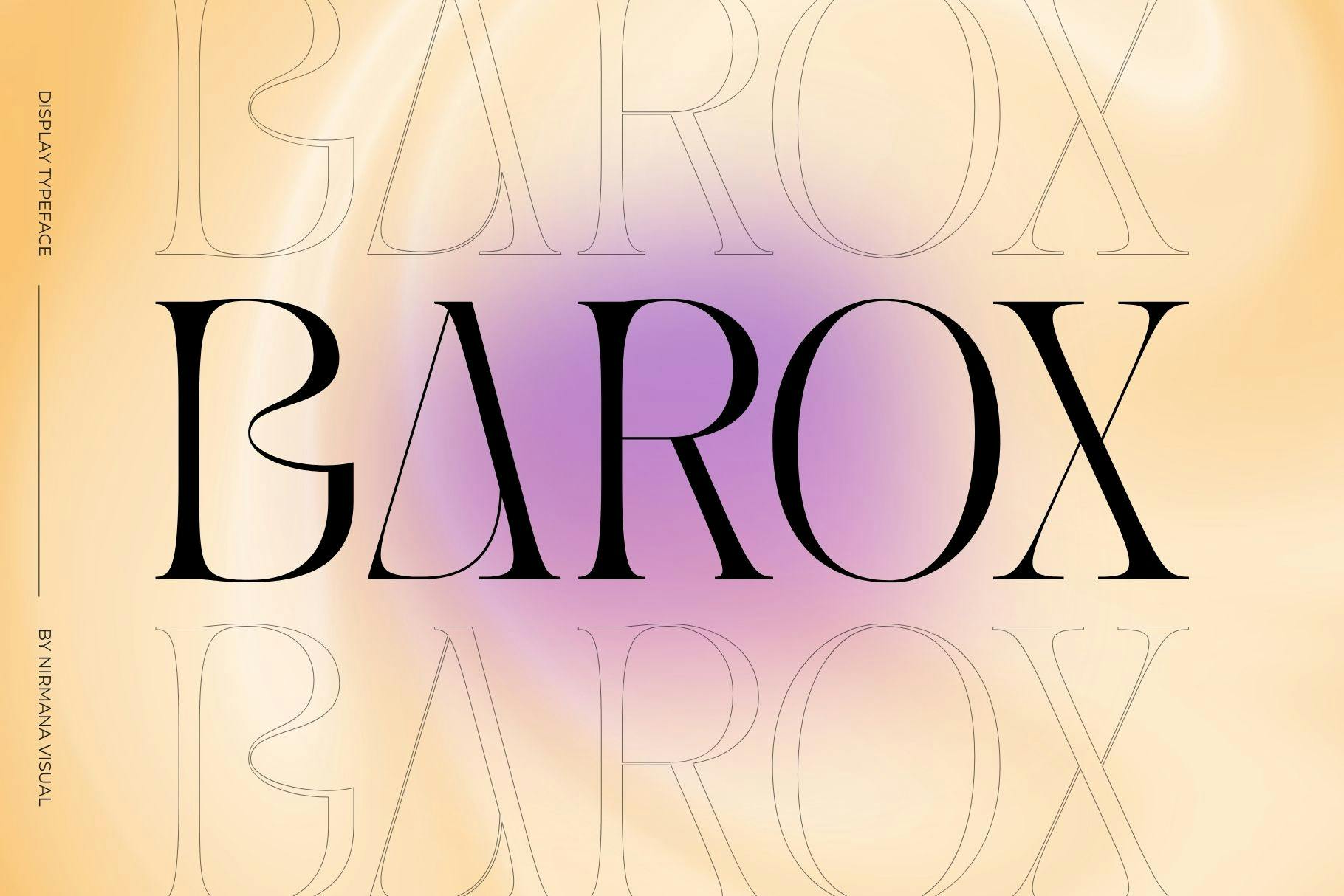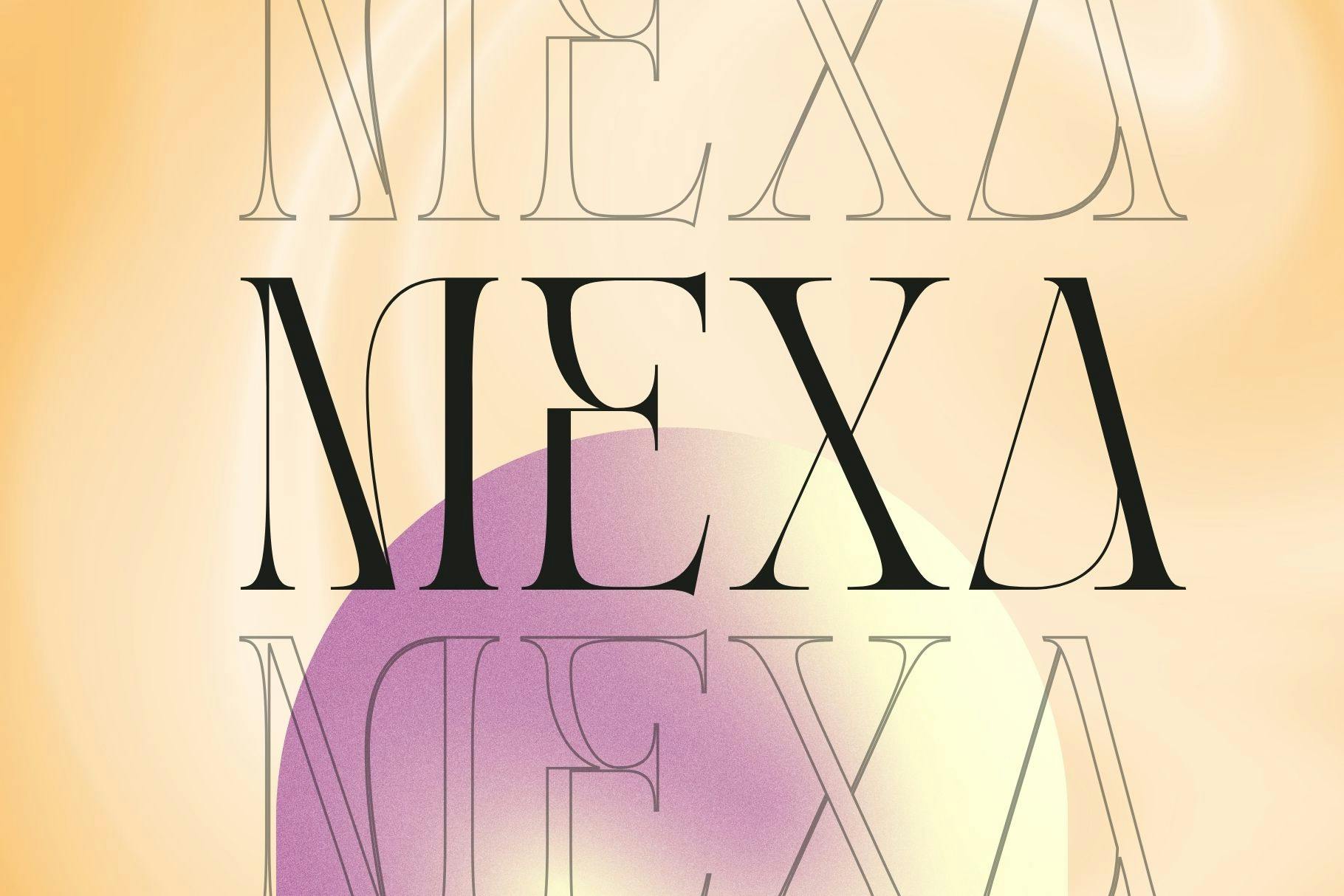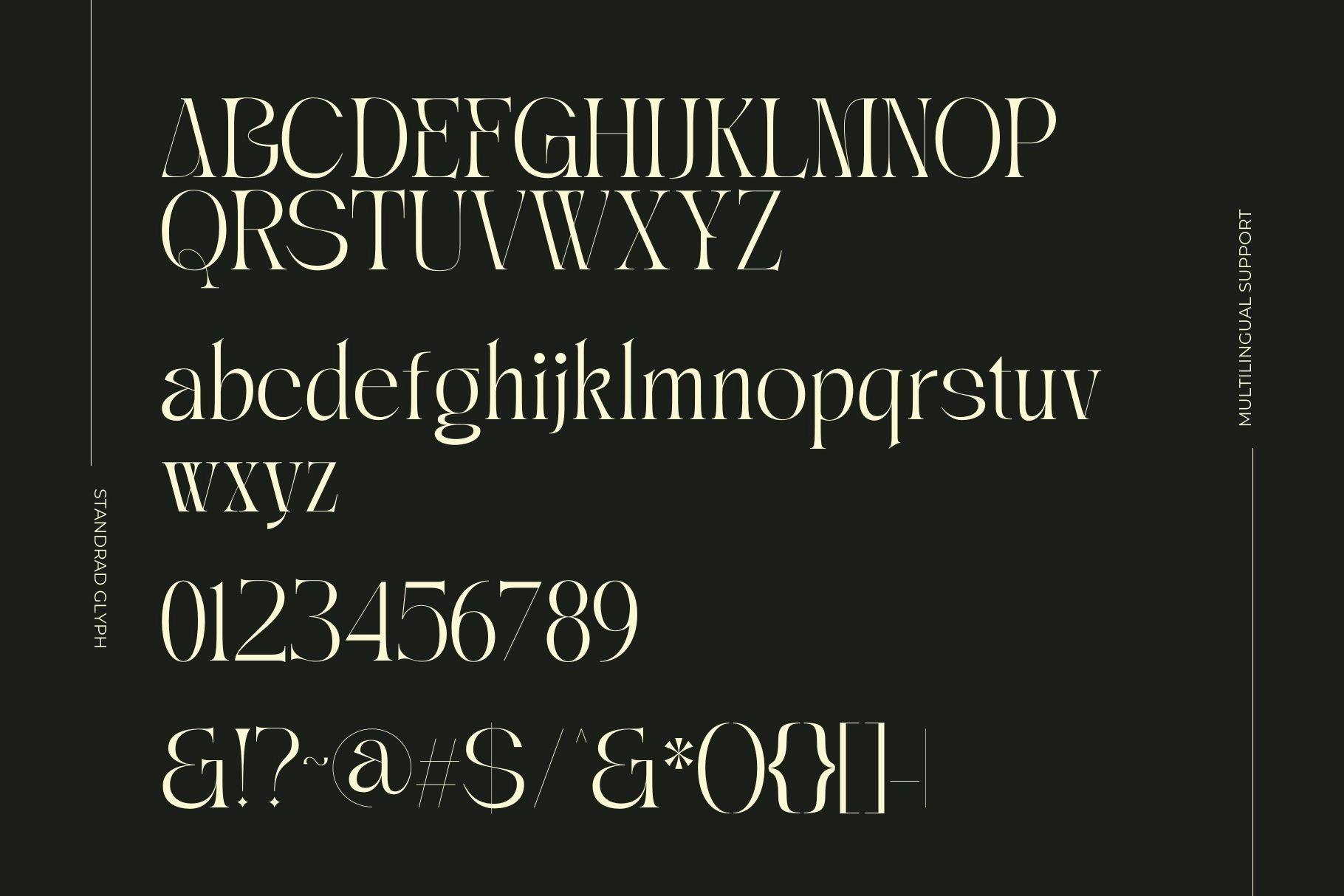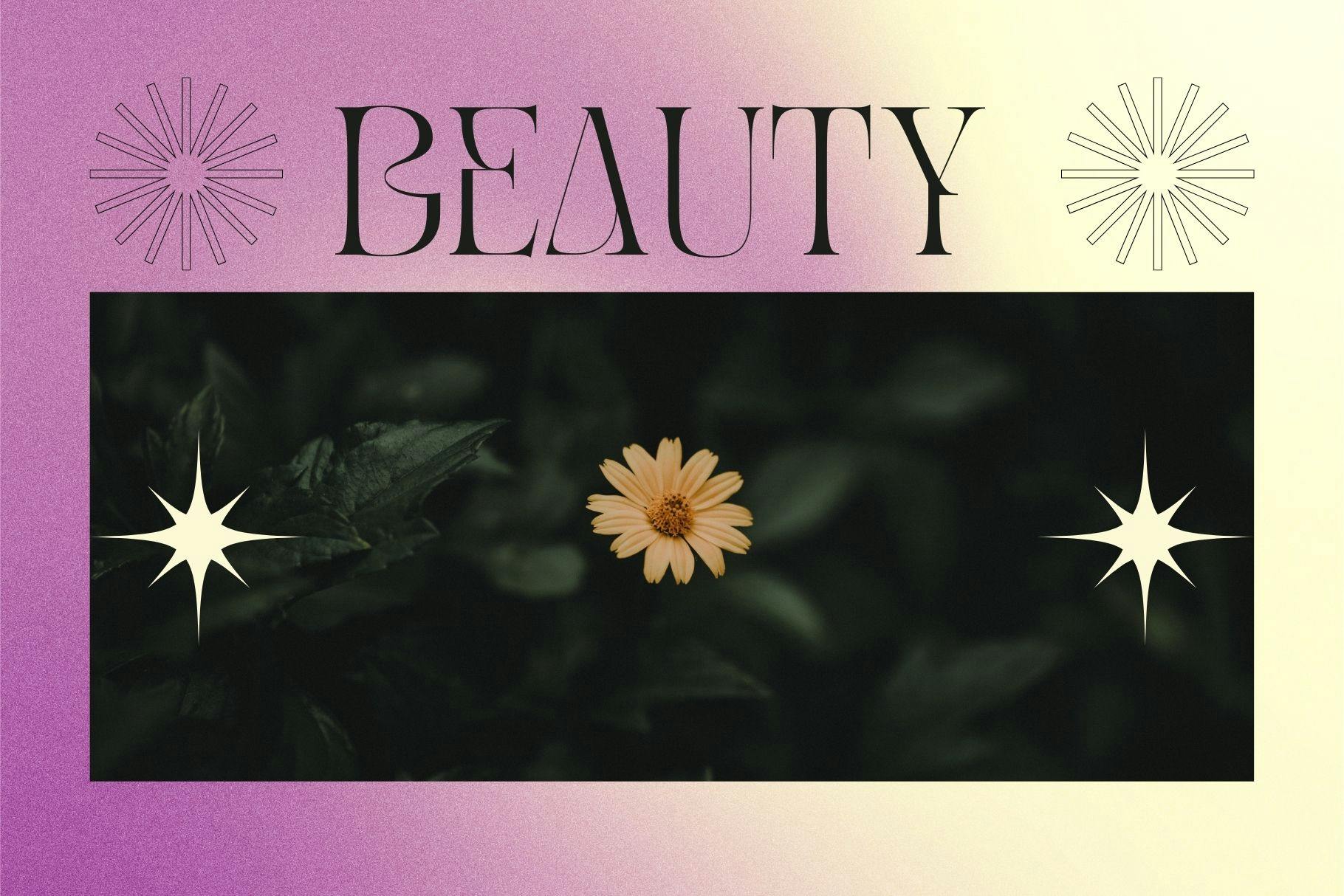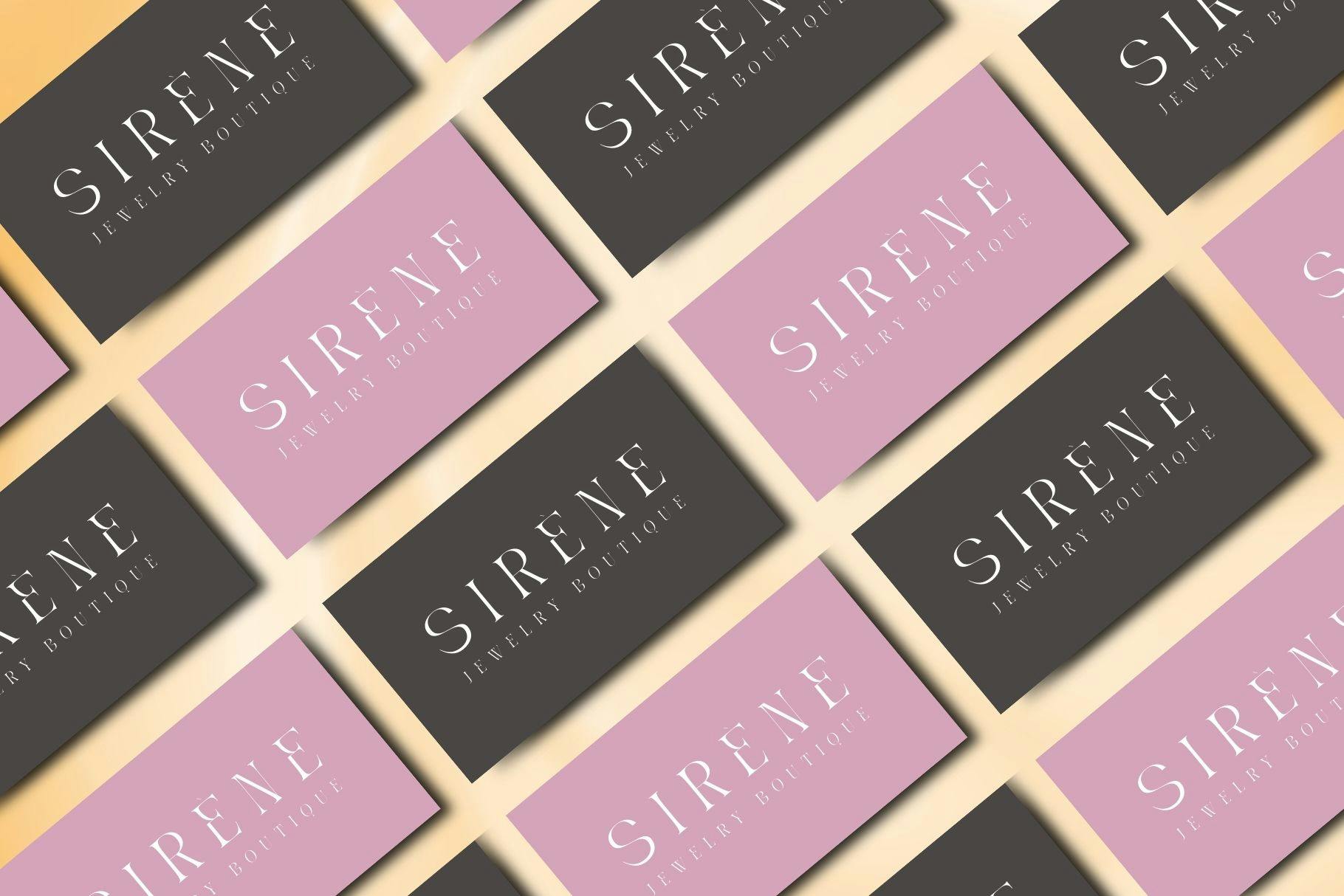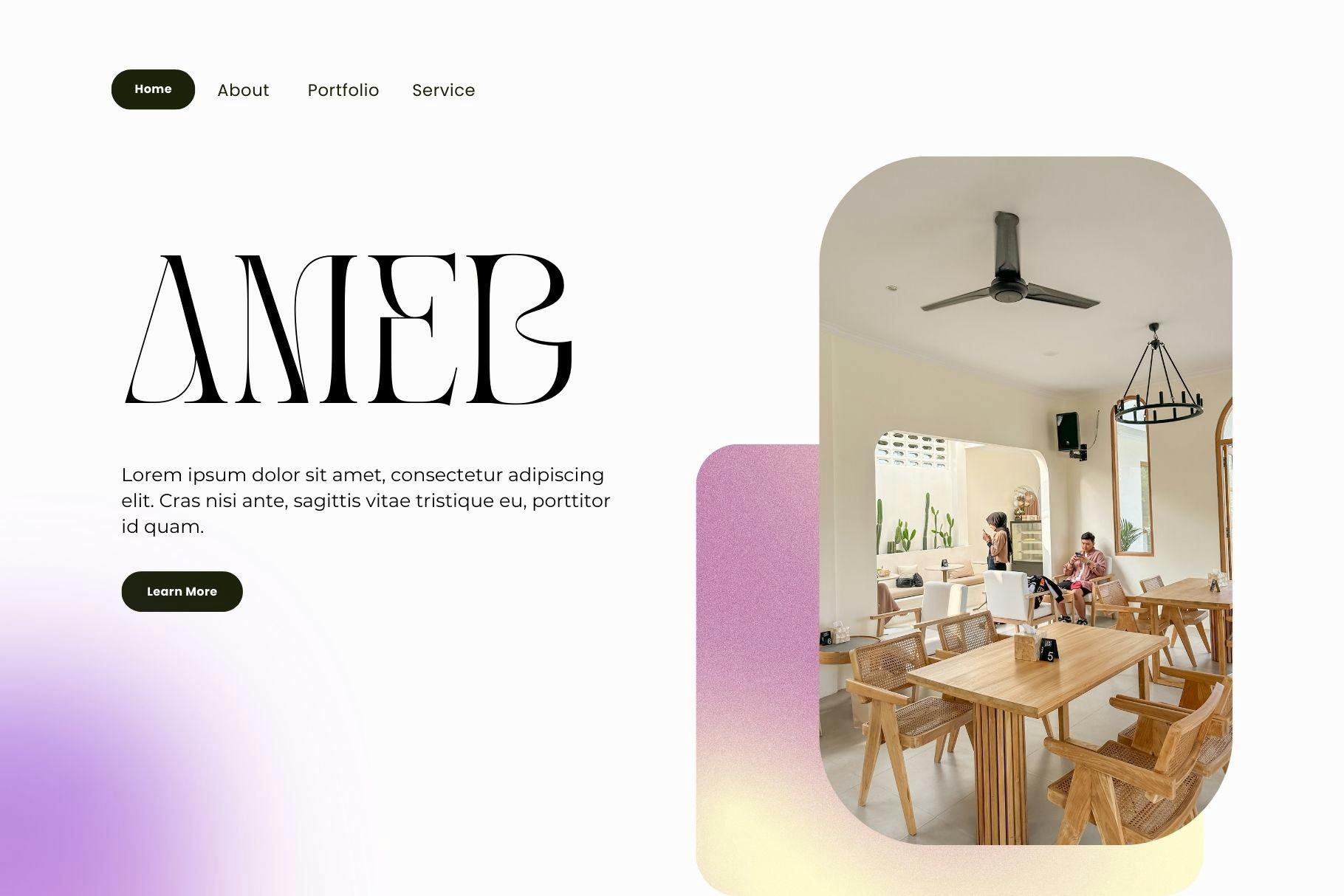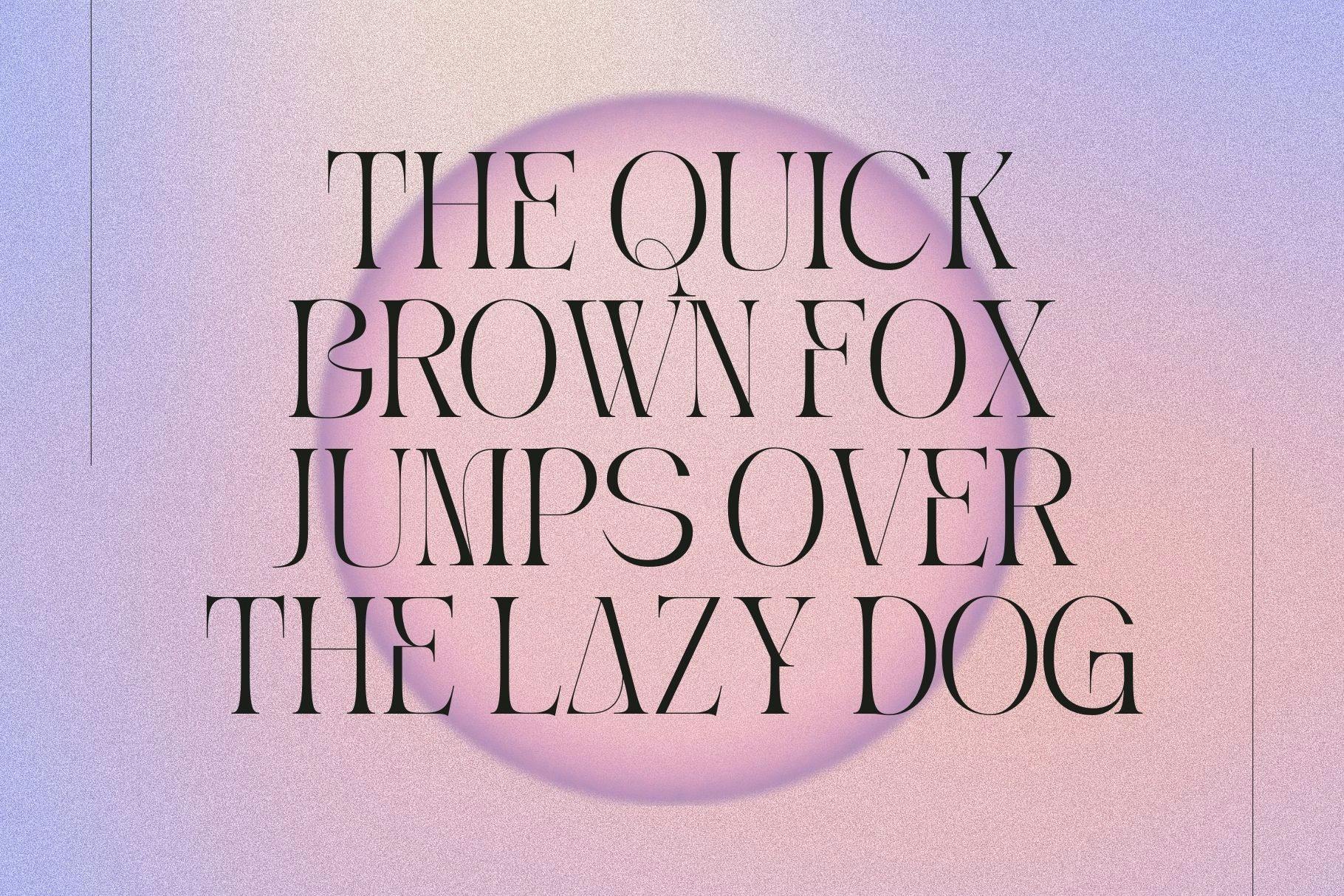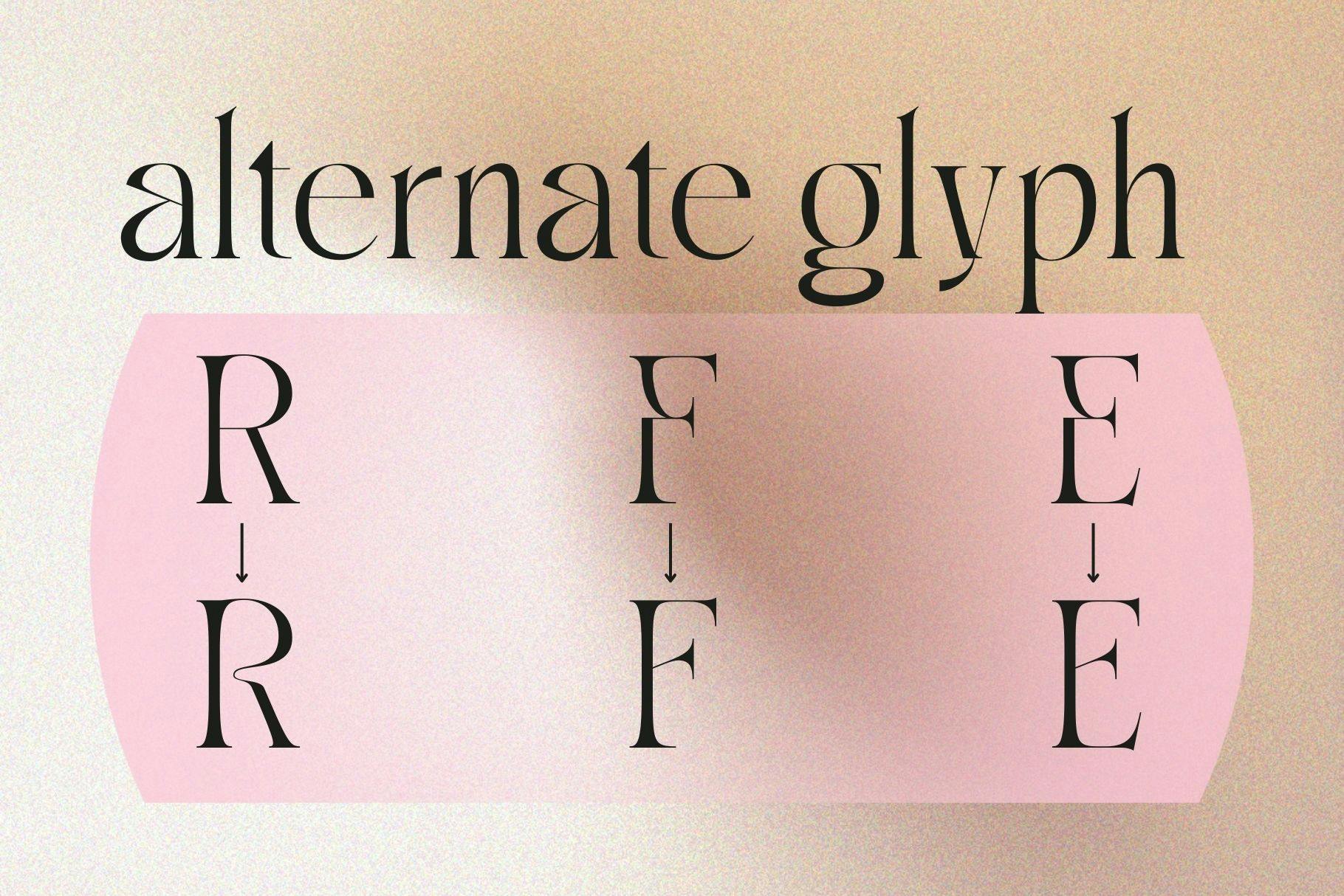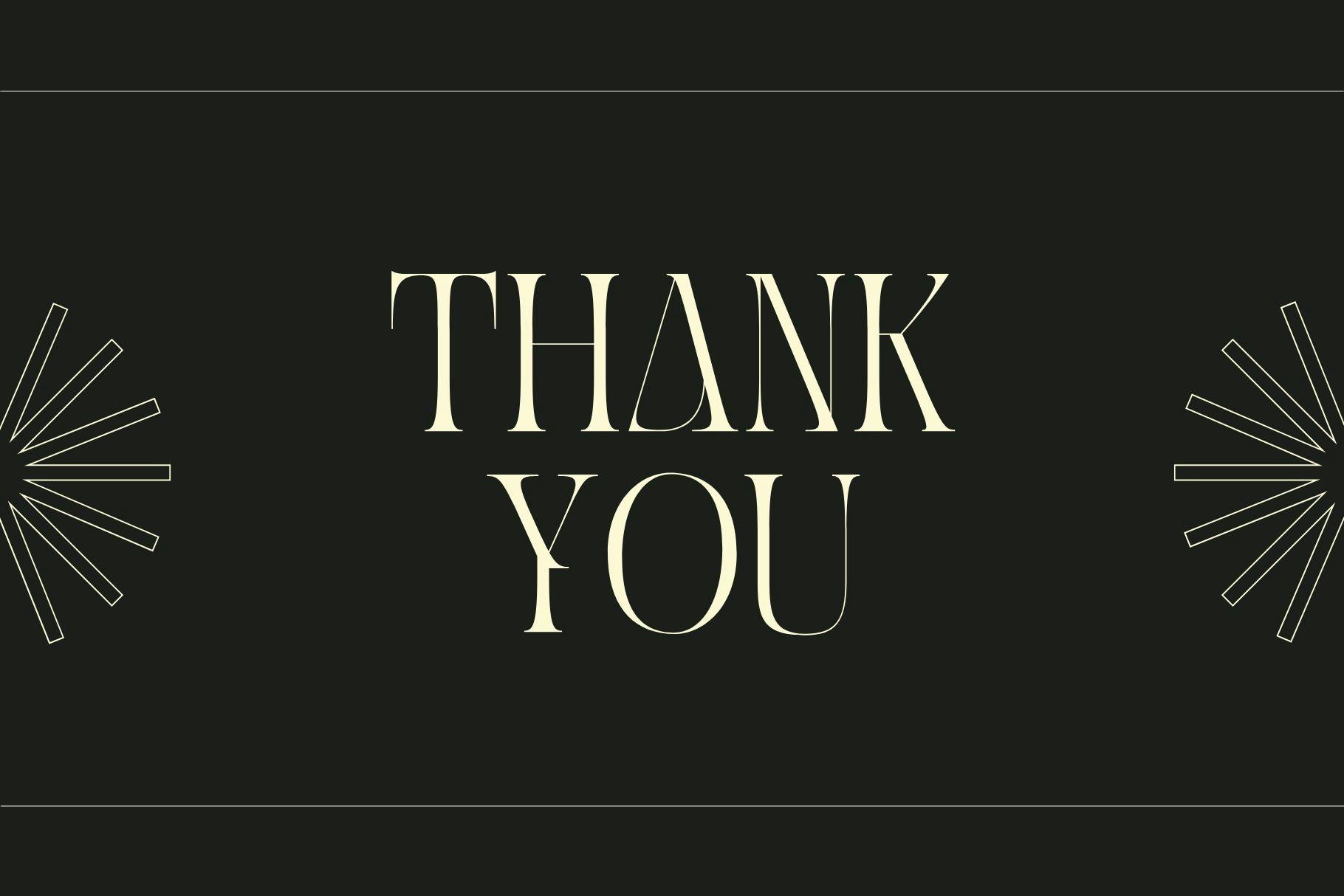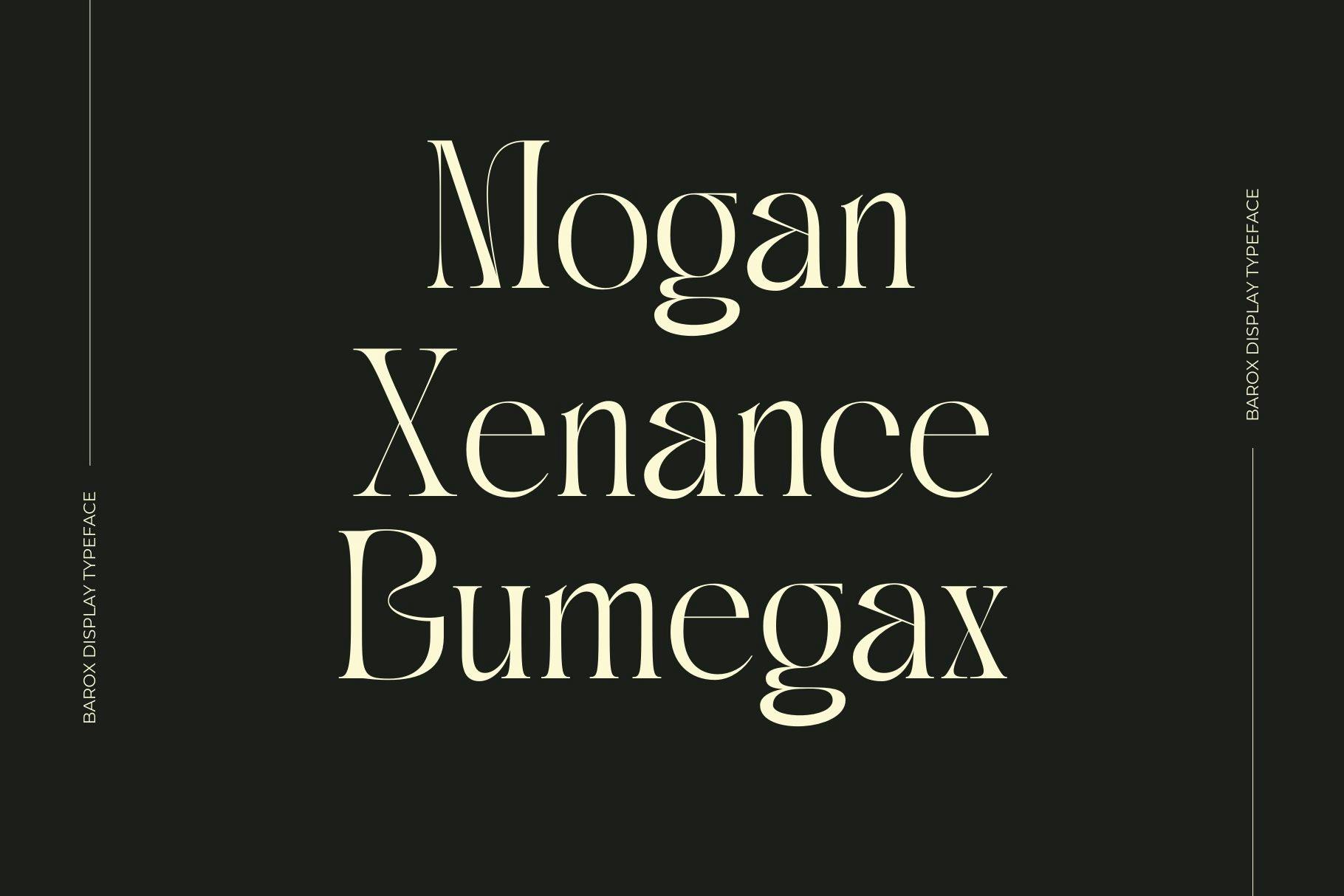
بارکس - فونت مدرن، نوع نوشته نمایشگر Serif.
فونت بارکس زیبایی و هماهنگی تایپوگرافیک را برای تنوعی از پروژههای طراحی، از جمله لوگو و برندینگ، پستهای شبکههای اجتماعی، تبلیغات و طراحی محصولات فراهم میکند.